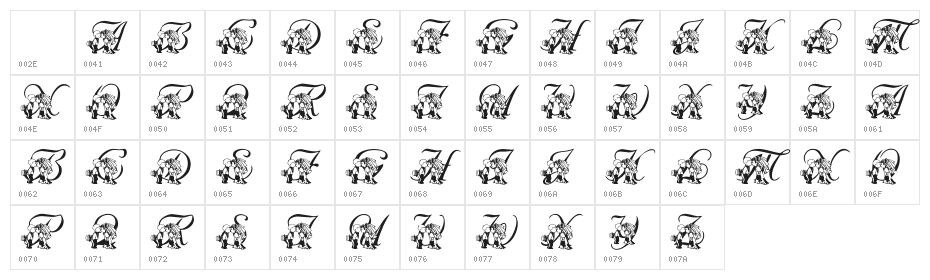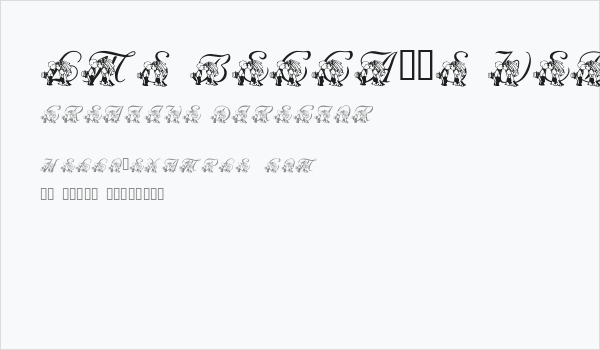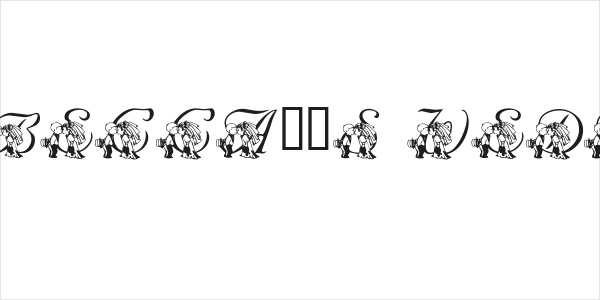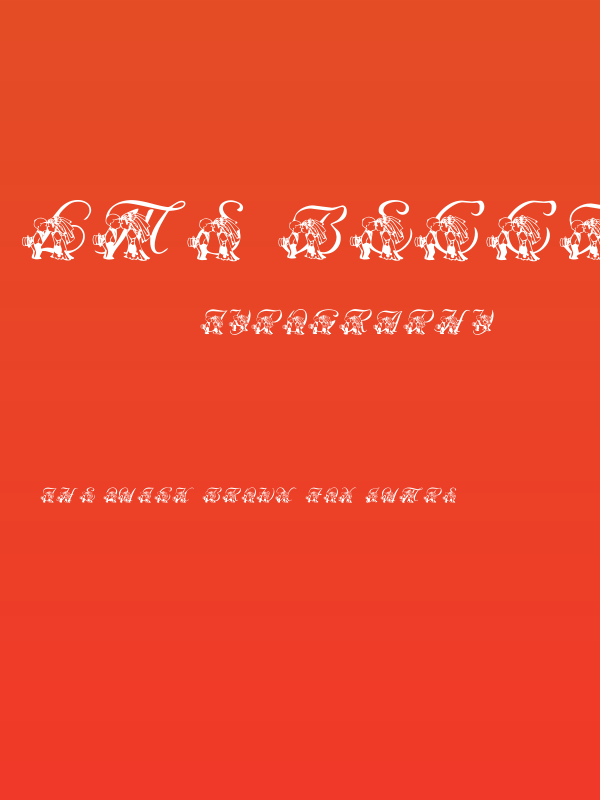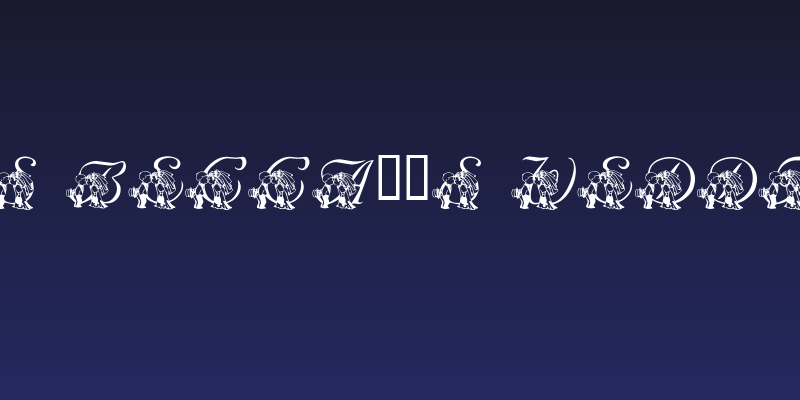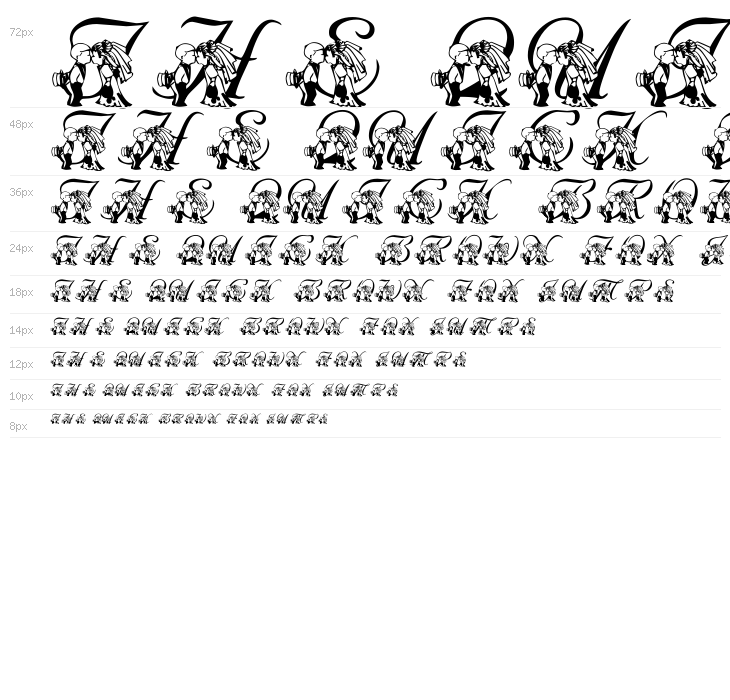
LMS Becca's Wedding Font
| Caso d'uso | Logos, Invitations, Decorative Text |
| Progetti proposti | Ideal for fantasy-themed invitations, children's book covers, or whimsical branding projects. |